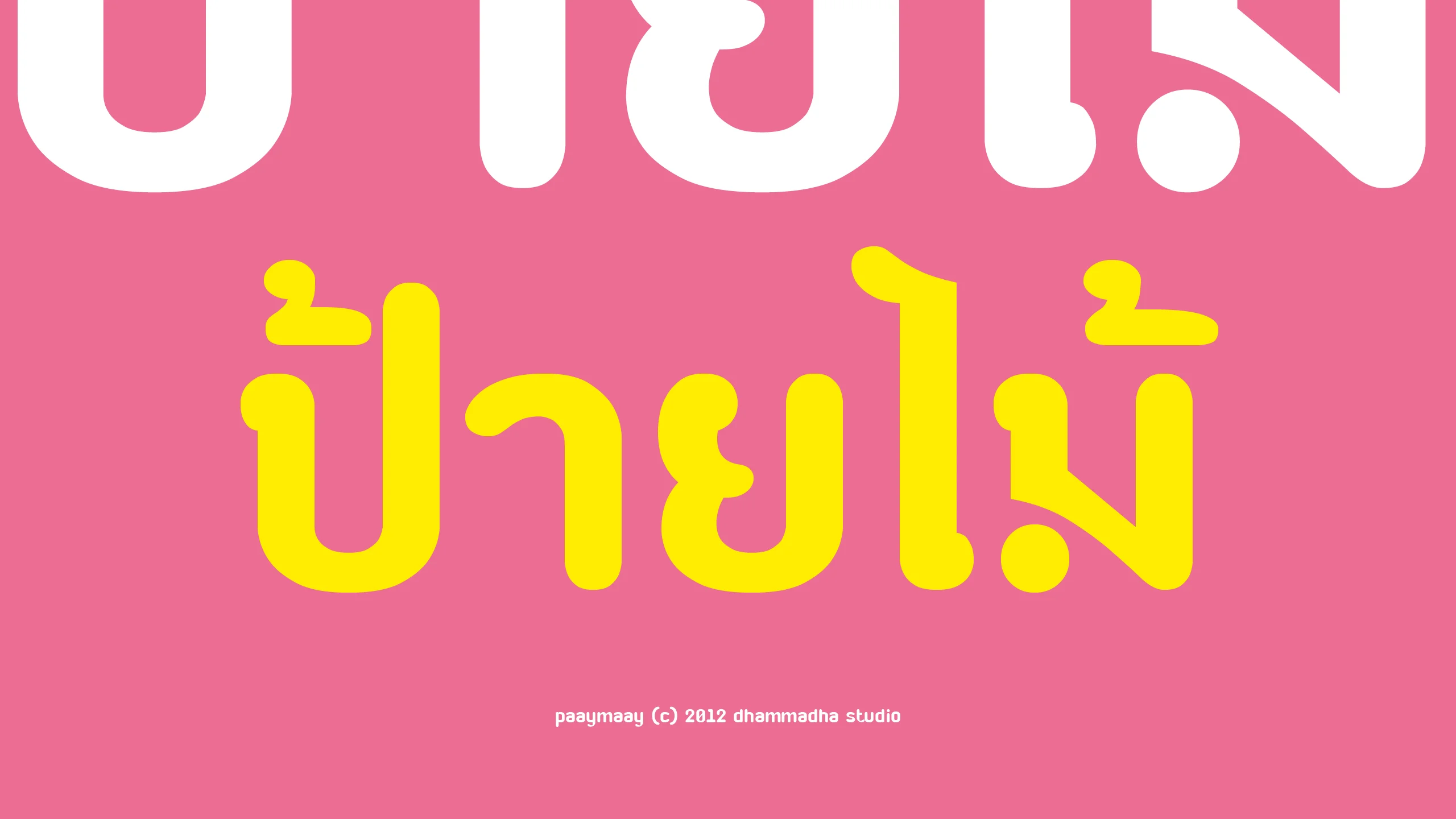
"ป้ายไม้ | paaymaay" เป็นฟอนต์แรกในชีวิตที่พัฒนาออกมาจนสำเร็จ ต้นแบบของฟอนต์ตัวนี้ คือ ป้ายทางเข้าสวนสาธารณะของเมืองสุราษฎร์ฯ (สวนศรีตาปี) ด้วยความชอบส่วนตัว และอยากเก็บฟอนต์เอาไว้ จึงนำรูปแบบหน้าตามาพัฒนาต่อเพื่อให้ใช้งานได้ง่ายขึ้น paaymaay เป็นฟอนต์ที่รับรางวัลผลงานระดับดีเด่น จากงาน Thai Typeface Design Competition #2 และนำมาพัฒนาต่อเพื่อให้สามารถใช้งานได้จริง paaymaay เป็นฟอนต์ที่มากับชุดอักษรทางเลือกอีกหนึ่งชุด เนื่องจากดีไซน์แรกของฟอนต์ อักษรไทยบางตัวอาจเกิดการสับสนเมื่อใช้งาน จึงได้พัฒนาชุดอักษรขึ้นมาใหม่ โดยให้ดีไซน์ดั้งเดิม ยังสามารถเลือกใช้ได้อยู่